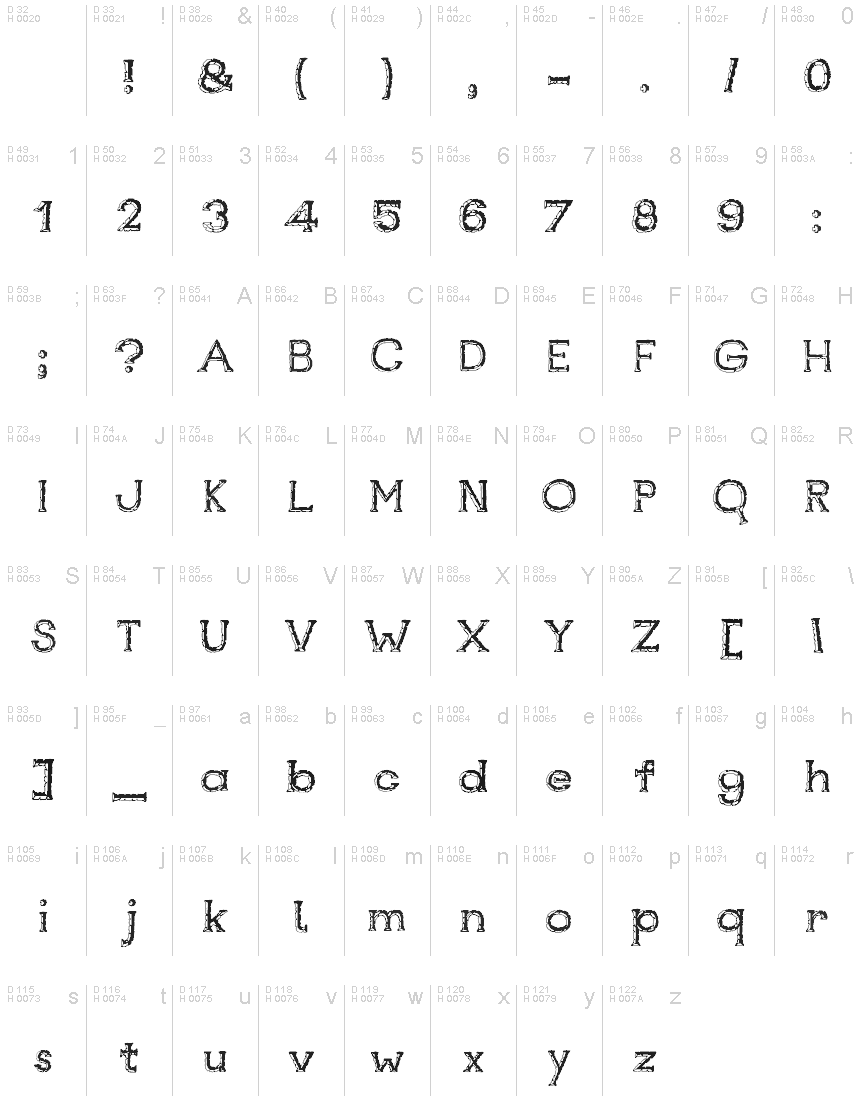
Rustswordsblack
Die Font ist fr headings gedacht und sollte auch fr diesen zweck Verwendung finden.
Bin Neu im Bereich der Schriftgestaltung und mchte einmal sehen wie diese Font bei anderen Nutzern ankommt.